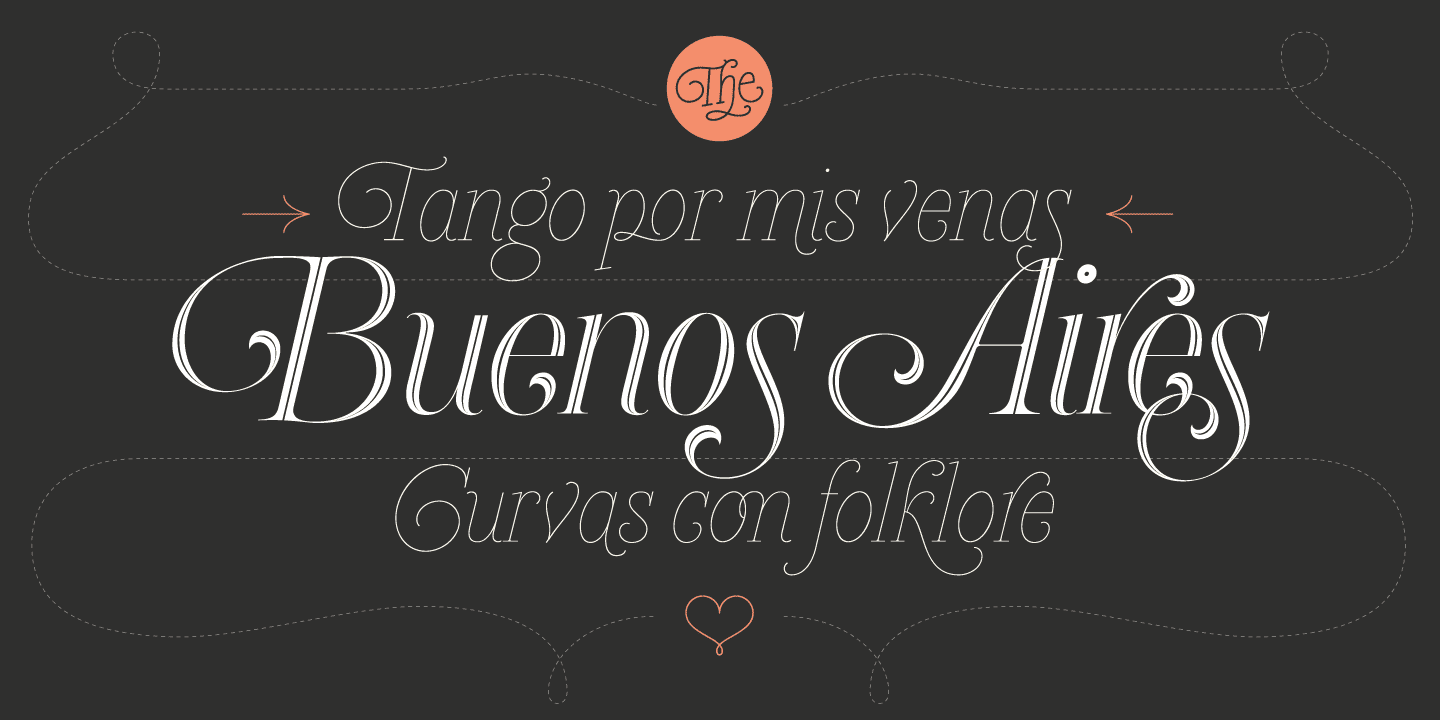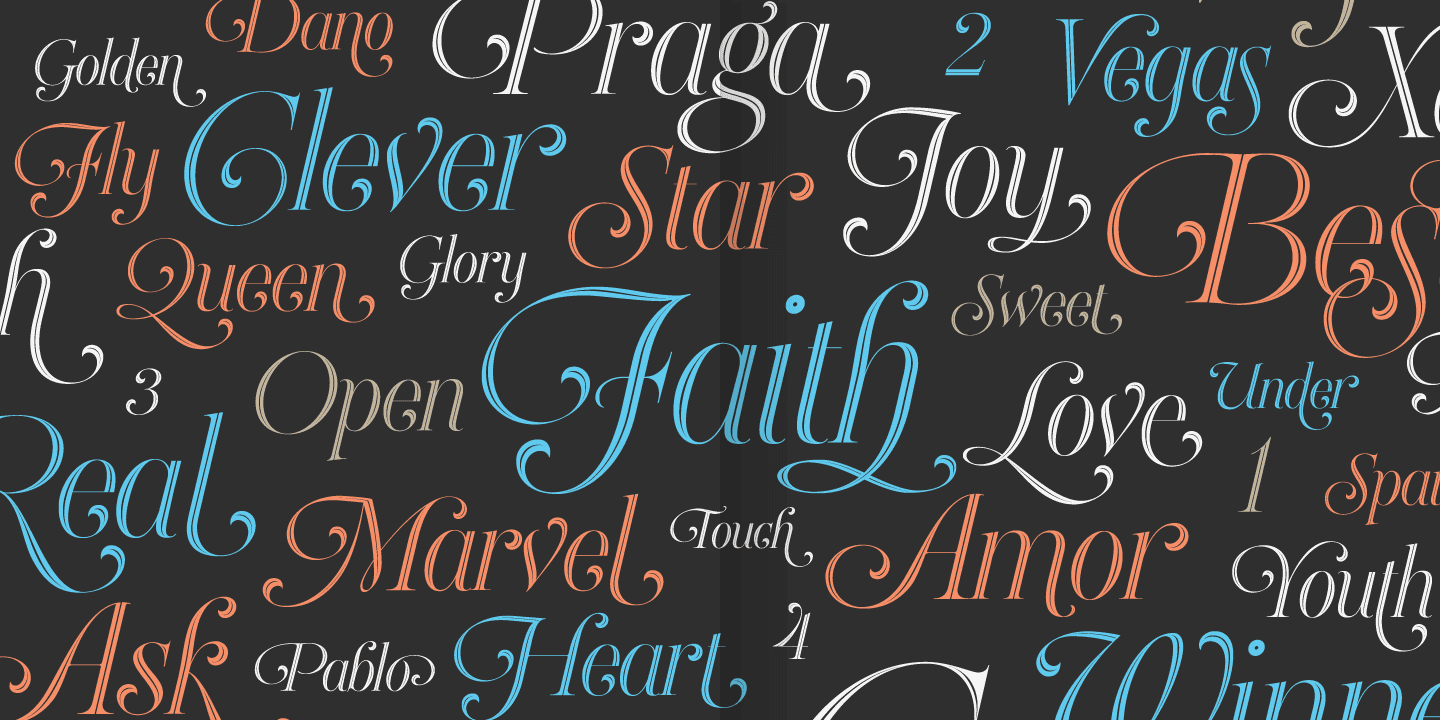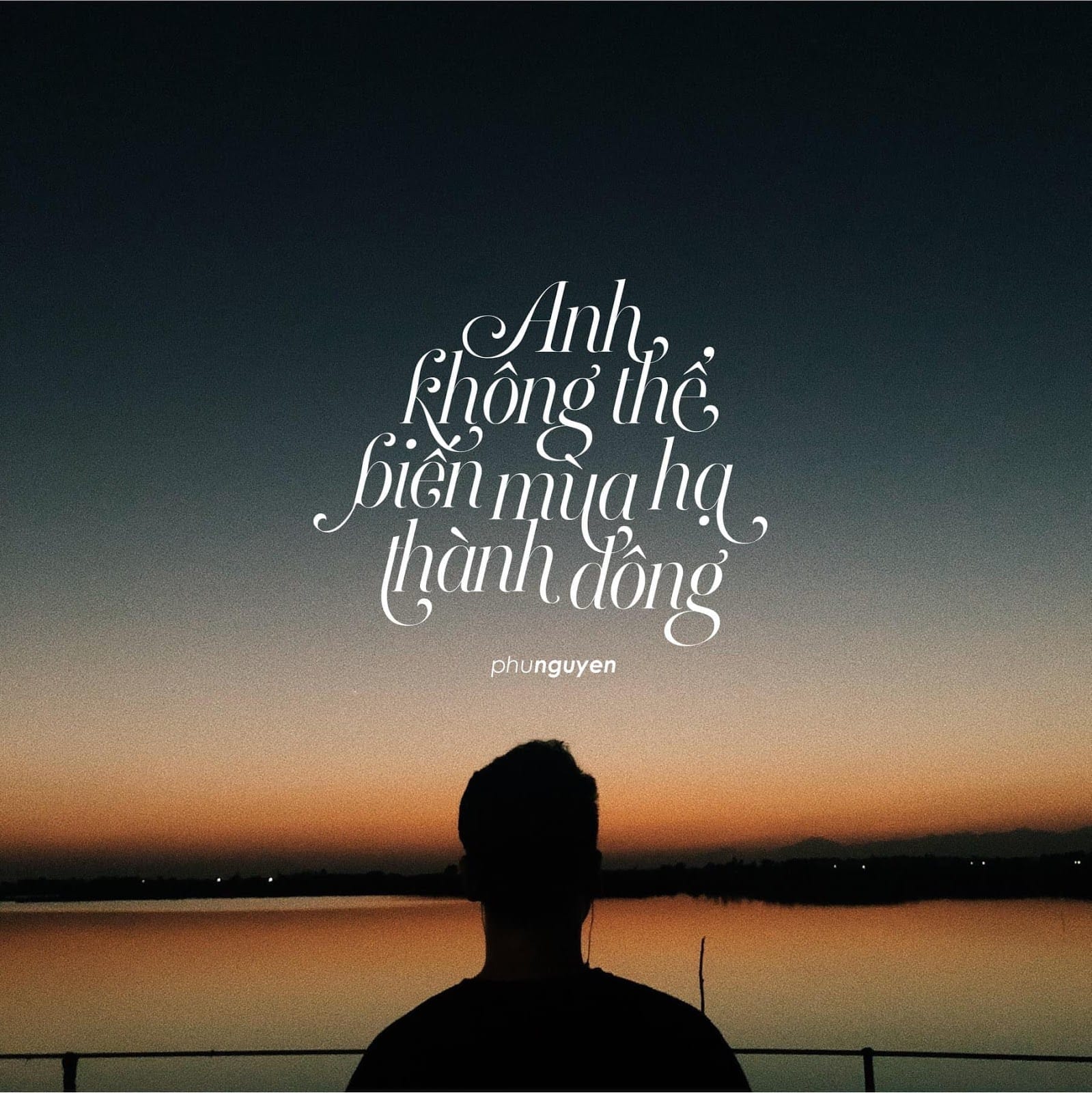
Heroe Pro Việt hóa là font chữ khá đẹp mắt với các đường nét thanh lịch và gợi cảm, bạn có thể sử dụng font này làm bìa tạp chí, thiệp mời… và đây là 1 trong những font chữ rất đẹp để làm typo.
Heroe, tiếng Tây Ban Nha có nghĩa là anh hùng, đưa một số khía cạnh của các loại font chữ roman lên tới mức cực đại giống như nguồn cảm hứng chính, nhà thiết kế vĩ đại Herb Lubalin, đã làm trong phần lớn các tác phẩm của ông: Các nét mảnh thành, tỷ lệ đã được điều chỉnh (được sử dụng cho mục đích trình bày), các đầu chữ đặc biệt, các đường cong thơ mộng và cách sắp xếp tinh tế của chúng trên bố cục. Phong cách lịch lãm của nó khiến font chữ trở nên hoàn hảo cho nhiều thiết kế khác nhau.
Hãy tưởng tượng kiểu Heroe Inline giống như nó đang nhảy múa trên một chai nước hoa; in trên bìa của một tạp chí thời trang; làm nổi bật trong thư mời cưới. Bản sao của nó, Heroe Monoline, có thể giúp bạn tạo ra các tác phẩm thiết kế phức tạp hơn. Chỉ cần kết hợp nó với Heroe, hoặc Heroe Inline và xem cách chúng hoàn hảo kết hợp với nhau.
Sự khác biệt giữa các kiểu Pro và Std là số lượng glyph. Trong khi các kiểu Pro có tất cả các ký tự trang trí có sẵn, các kiểu Standard chỉ có bộ ký tự cơ bản của chúng. Heroe Monoline Big và Heroe Monoline Small được tạo ra để in ấn tốt hơn. Nếu bạn cần in font chữ ở kích thước nhỏ, thì lựa chọn của bạn nên là Small. Heroe Monoline có các phần thay thế giống như Heroe Pro và Inline, cộng với một số ký tự ghép trang trí.